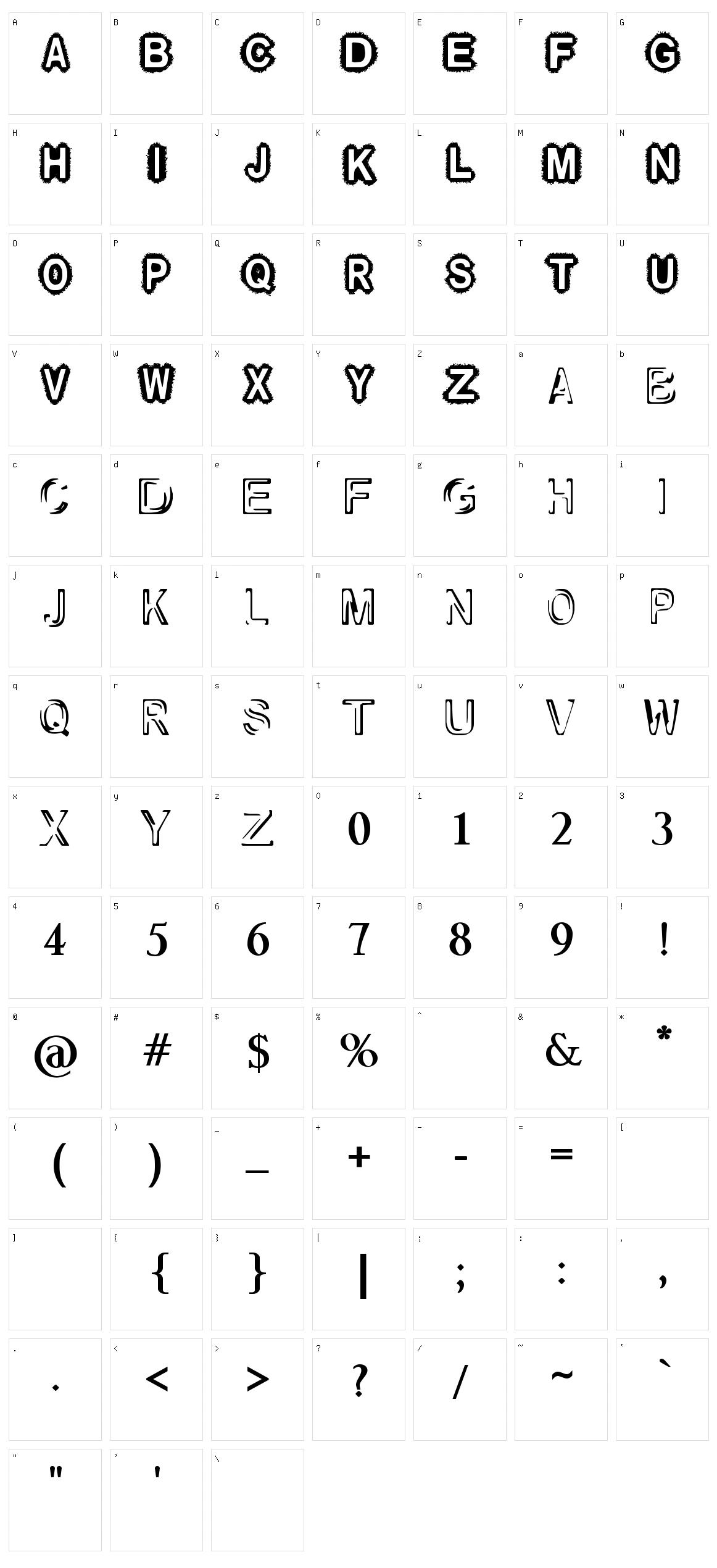
Vous venez d'aquérir à peu près légalement le font (police) "Raslani und so weiter"
Il s'agit d'une écriture d'abord manuscrite puis scanée et assemblée pour en faire une police pour vos documents,
vos montages, ou autres choses dans le même goût.